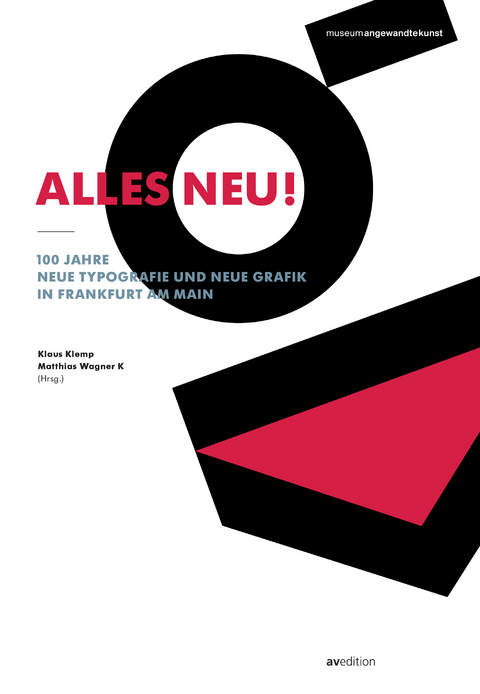
Alles neu! 100 Jahre Neue Typografie und Neue Grafik in Frankfurt am Main
Nach dem Ersten Weltkrieg entstand in Frankfurt ein einzigartiges Modernisierungs- und Gestaltungsprojekt, das als "Das Neue Frankfurt" in die Architekturgeschichte eingegangen ist. Das Museum Angewandte Kunst erweitert die Sicht auf "Das Neue Frankfurt" um den Bereich des Designs und rückt im Frühjahr 2016 Typografie und Grafik in den Fokus.Aus Frankfurt stammen Meilensteine der visuellen Gestaltungsmoderne: So wurde etwa in den 1920er-Jahren die erste populäre Reformschrift Futura in der Mainmetropole entworfen und trat von hier aus ihren weltweiten Siegeszug an. Nach 1945 war Frankfurt nicht zuletzt durch die Ansiedlung US-amerikanischer Werbeagenturen, durch Verlage wie Suhrkamp und S. Fischer und den Einfluss der Kasseler Plakatschule ein Hotspot des typografischen und werbegrafischen Geschehens der Zeit - und ist es heute.